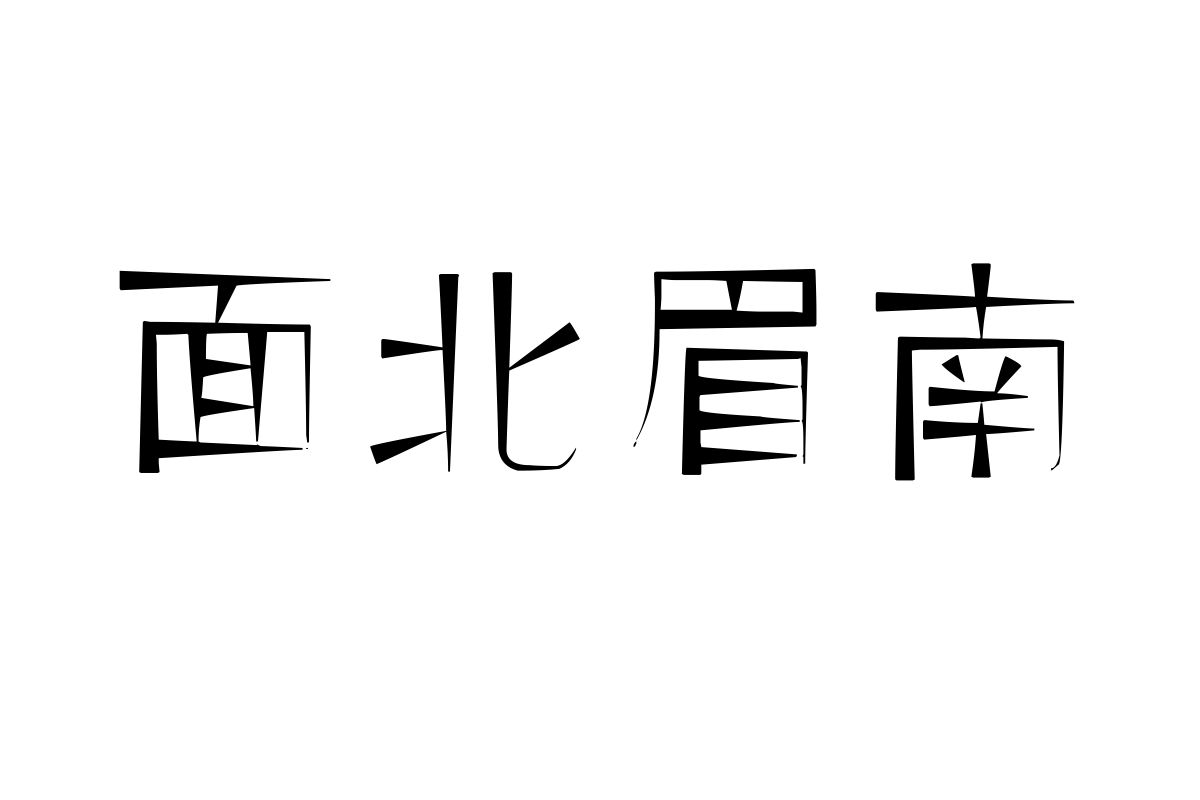
汉标三角体是一种具有独特设计的字体,其特点是在字母的顶部和底部添加了三个小三角形。这种设计使得字体看起来更加立体和有趣,给人一种视觉上的冲击力。
汉标三角体的字体特点如下:
1. 独特的设计:汉标三角体在字母的顶部和底部添加了三个小三角形,使得字体看起来更加立体和有趣。
2. 易于阅读:虽然汉标三角体的设计独特,但它仍然保持了良好的可读性,适用于各种印刷和电子媒体。
3. 适用场景广泛:汉标三角体适用于广告、包装、标志等多种应用场景,可以为企业和个人提供个性化的视觉表达。
总之,汉标三角体是一种独特而有趣的字体,适用于各种设计和印刷需求,为个人和企业提供了丰富的视觉选择。